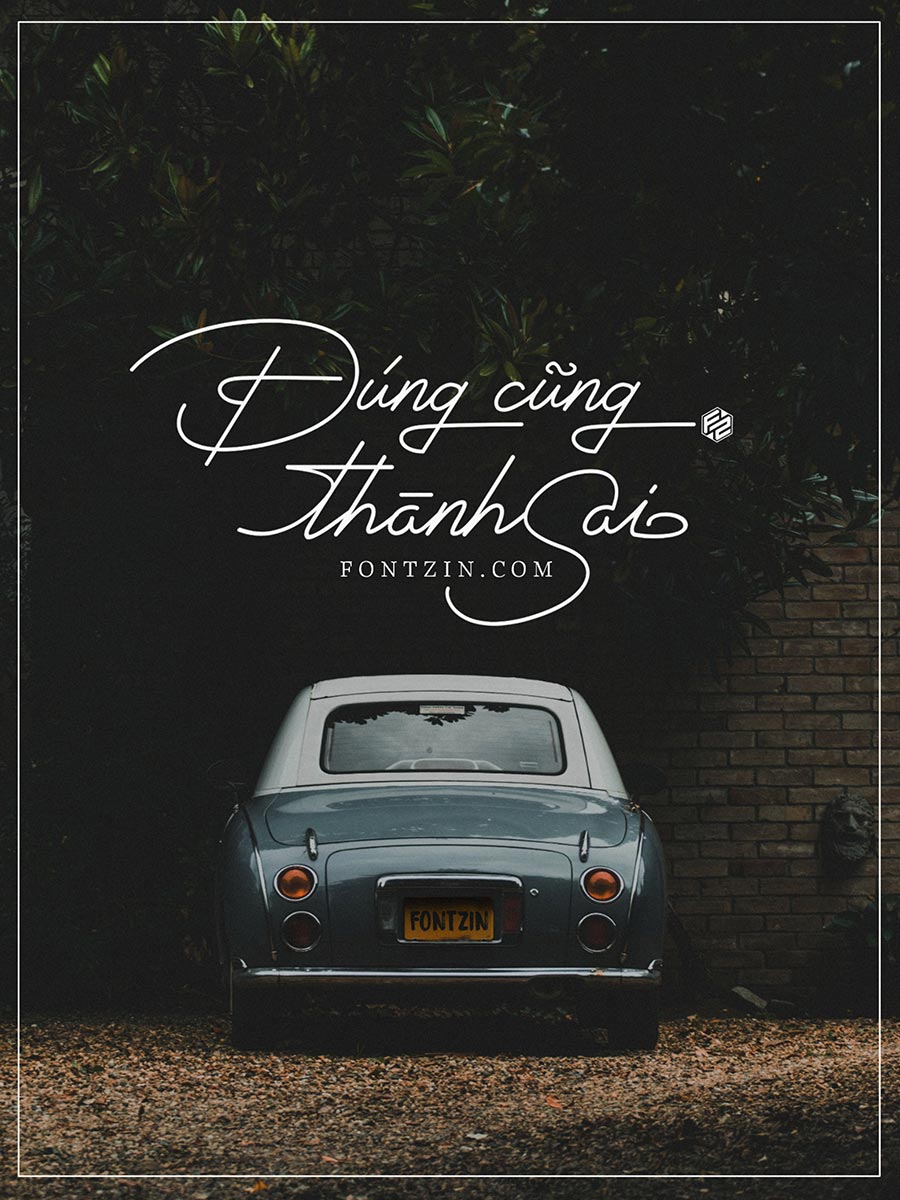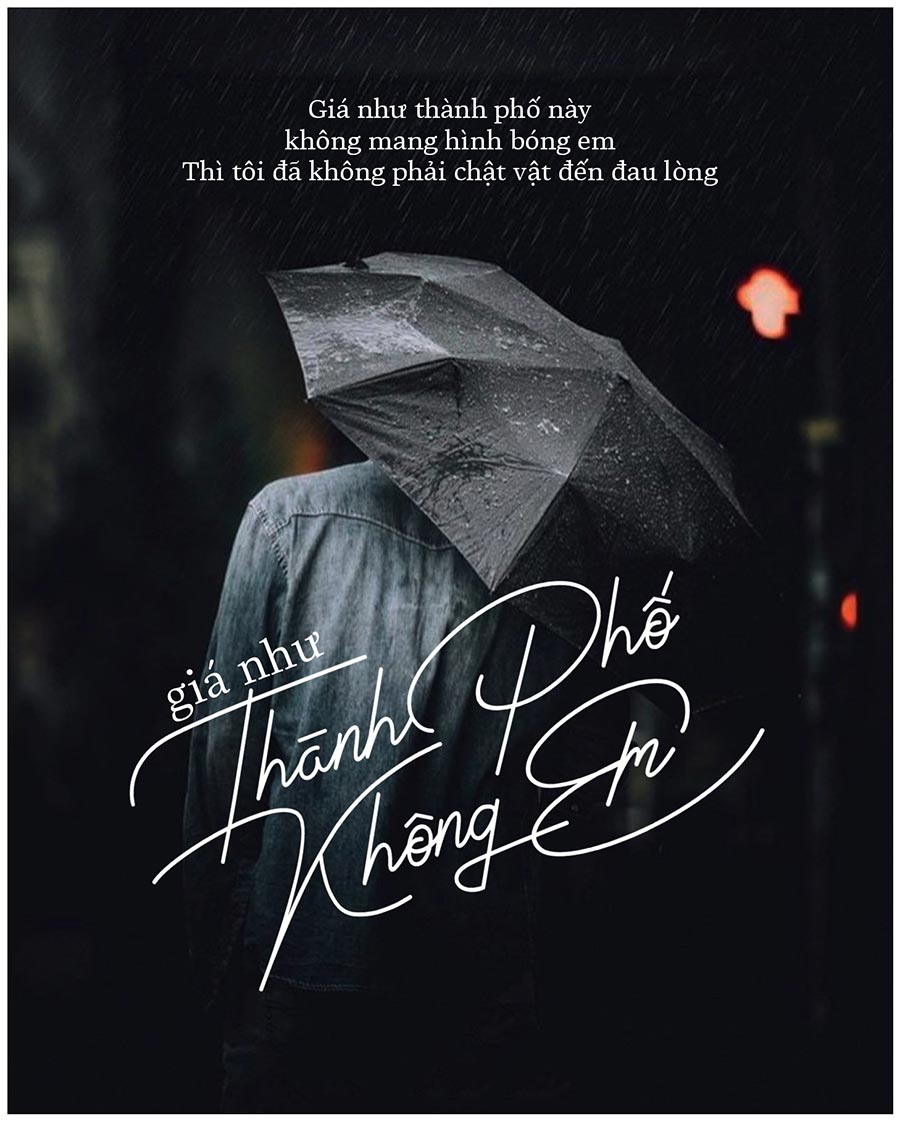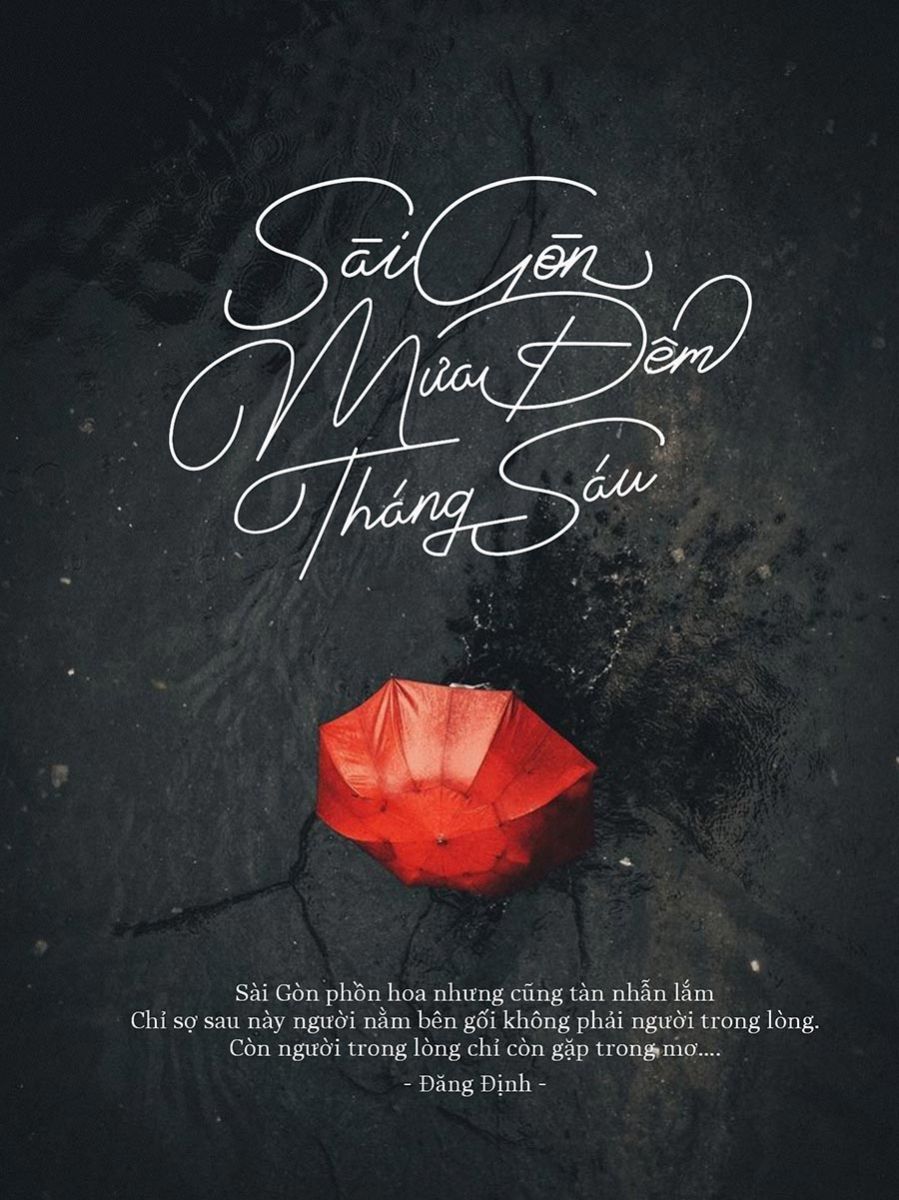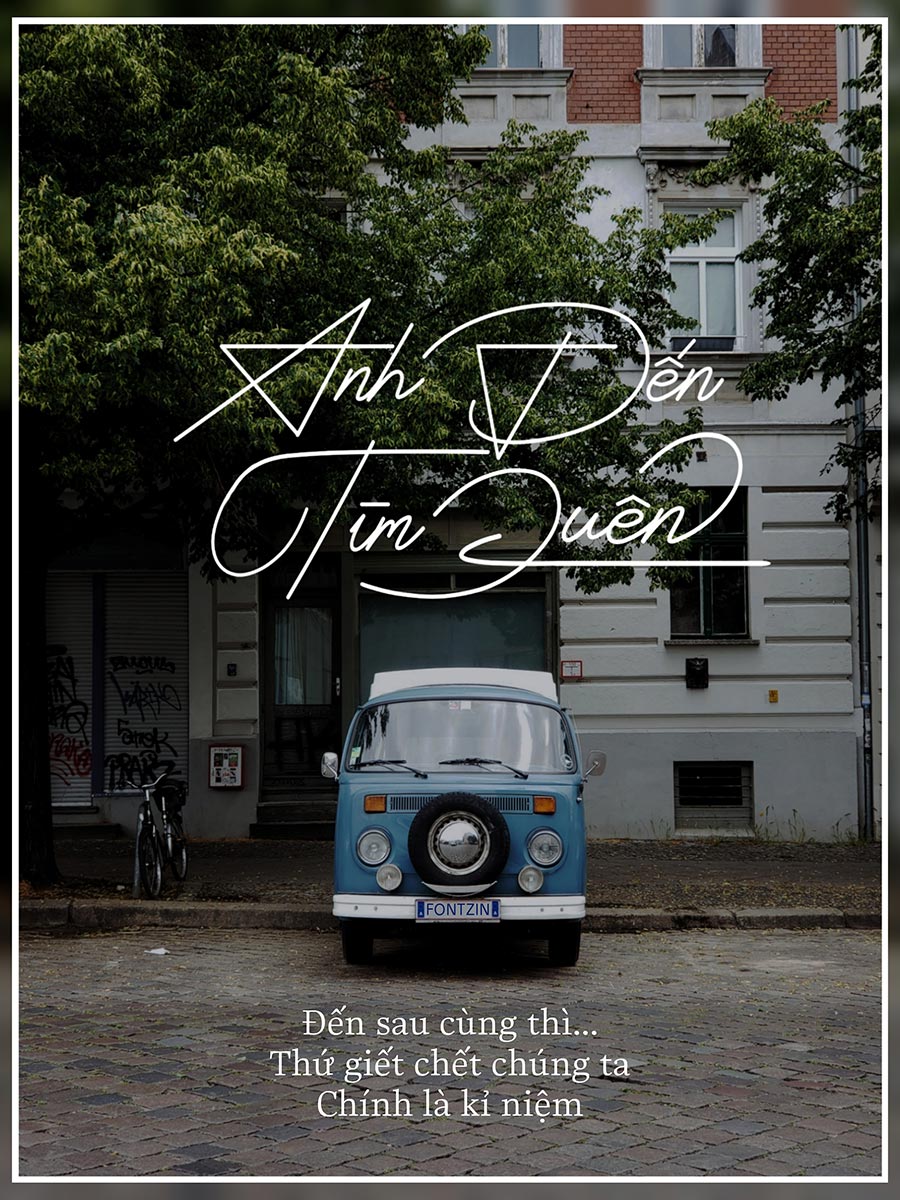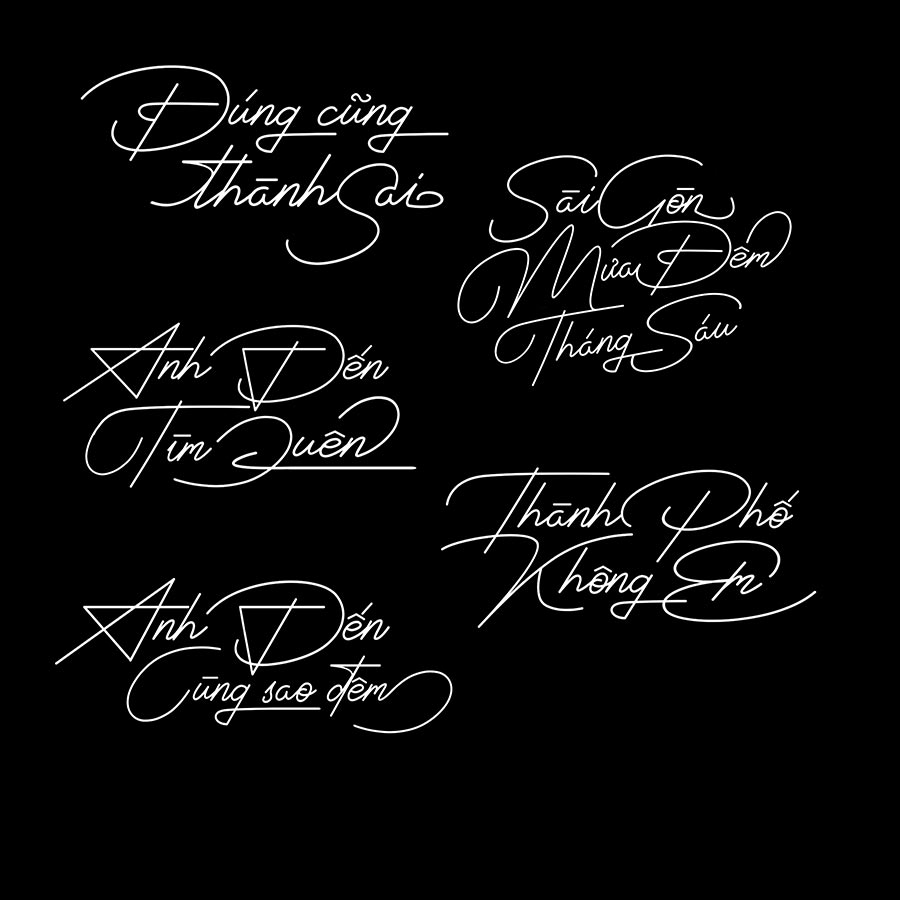
Với xu hướng hiện đại, các font chữ ký đang ngày càng được ưa chuộng bởi sự tinh tế, sang trọng và mang tính cá nhân hóa cao. Một trong những font chữ ký nổi bật hiện nay là **Presidente**, nay đã được Việt hóa hoàn chỉnh và chia sẻ miễn phí bởi Sadesign.vn.
Giới thiệu về Font Presidente
Font Presidente là một font chữ ký với thiết kế mềm mại, uyển chuyển nhưng không kém phần mạnh mẽ. Font này được phát triển nhằm mang lại cảm giác chuyên nghiệp, đẳng cấp và phù hợp với nhiều mục đích sử dụng khác nhau như: thiết kế logo, thiệp mời, tiêu đề bài viết, hoặc thậm chí là các sản phẩm thương hiệu cá nhân.
Font Presidente nổi bật nhờ các đường nét mô phỏng chữ viết tay tự nhiên, tạo cảm giác gần gũi nhưng vẫn giữ được sự tinh tế. Khi được Việt hóa, font này không chỉ hỗ trợ đầy đủ các ký tự tiếng Việt mà còn đảm bảo tính thẩm mỹ và hài hòa trong từng chi tiết.
Ưu điểm của Font Presidente Việt Hóa
1. Hỗ trợ đầy đủ tiếng Việt: Với bộ ký tự tiếng Việt được Việt hóa cẩn thận, font Presidente hoàn toàn phù hợp cho các dự án thiết kế phục vụ thị trường Việt Nam.
2. Thẩm mỹ cao: Các đường nét mềm mại, uyển chuyển giúp font chữ này trở thành lựa chọn lý tưởng cho những thiết kế cần sự tinh tế và sang trọng.
3. Dễ dàng ứng dụng: Font Presidente có thể sử dụng trong nhiều lĩnh vực như thiết kế đồ họa, in ấn, quảng cáo, truyền thông hay thậm chí là làm nội dung số.
Kết luận